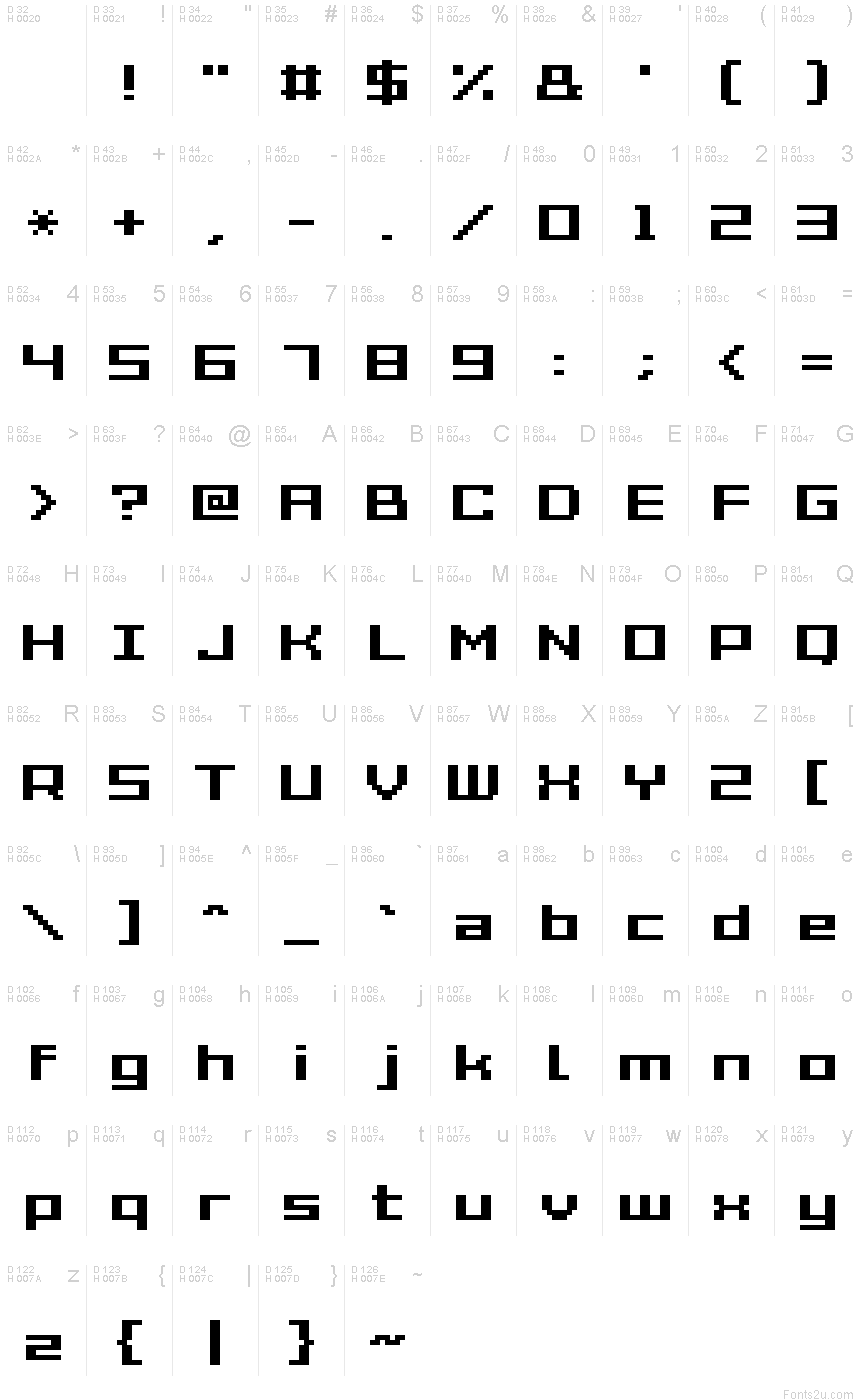
Grixel Acme 7 Wide Bold
<p>Grixel Acme 7 Wide Bold od Grixel – Greek Pixel Fonts to darmowy font bitmapowy z rodziny Grixel Acme 7. Jego litery są przysadziste, masywne i szerokie, idealnie wpisane w surową siatkę, która przywodzi na myśl świecący szyld automatu arcade. Śmiałe, równomiernie wyważone linie nadają każdemu słowu solidny, mechaniczny rytm, który pozostaje czytelny nawet przy niewielkim rozmiarze na ekranie.</p>
<p>Grixel Acme 7 Wide Bold to gotowy styl dla tytułów gier retro, oznaczeń HUD, stron pixel-artowych, plakatów synthwave, technicznych nakładek na streamy czy przycisków UI. Ten darmowy krój najlepiej sprawdza się w dużym rozmiarze jako nagłówek. Warto zestawić go z prostym krojem bezszeryfowym w dłuższych tekstach, aby zachować czytelność układu, pozwalając jednocześnie pikselowej teksturze budować klimat.</p>